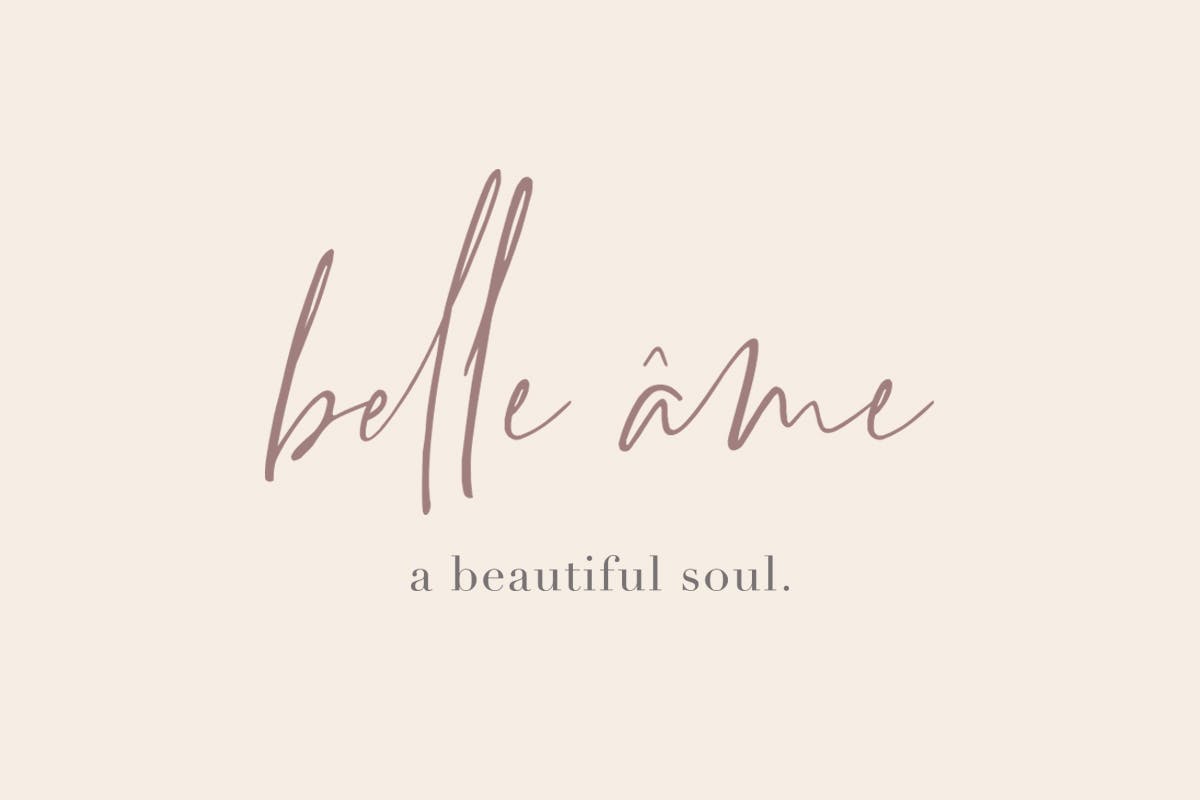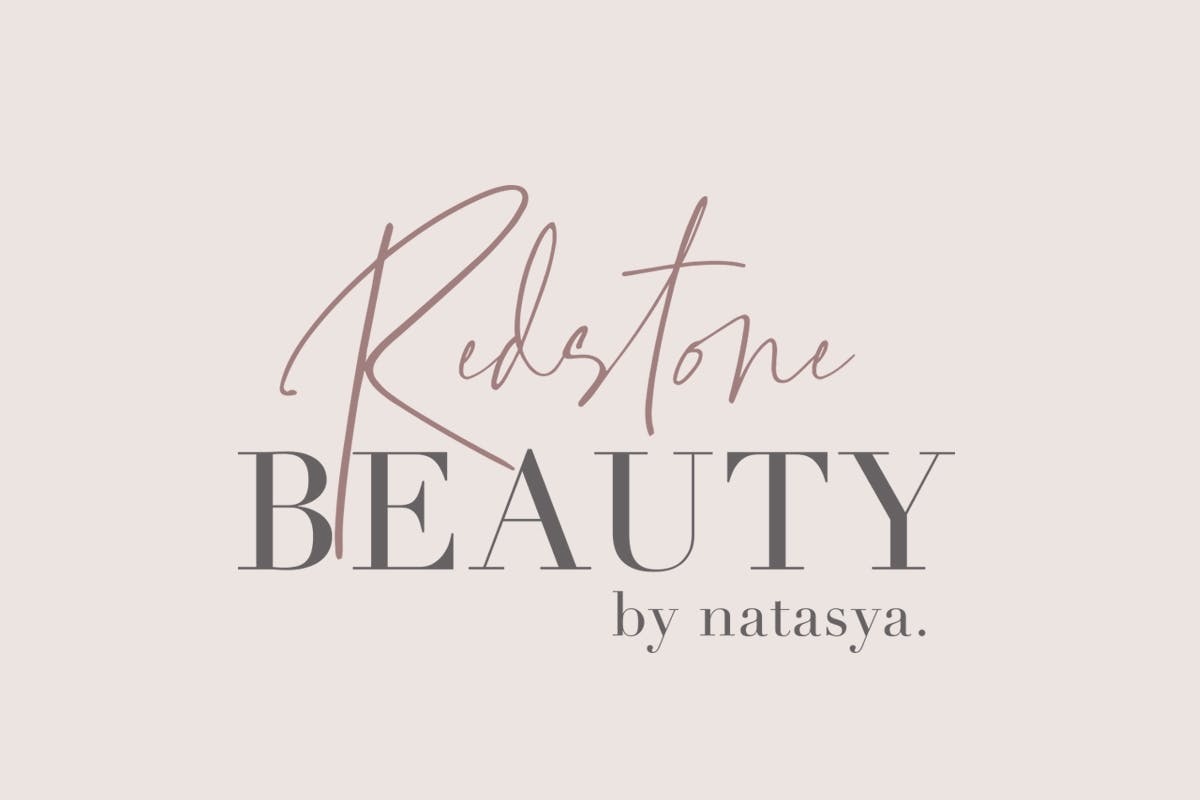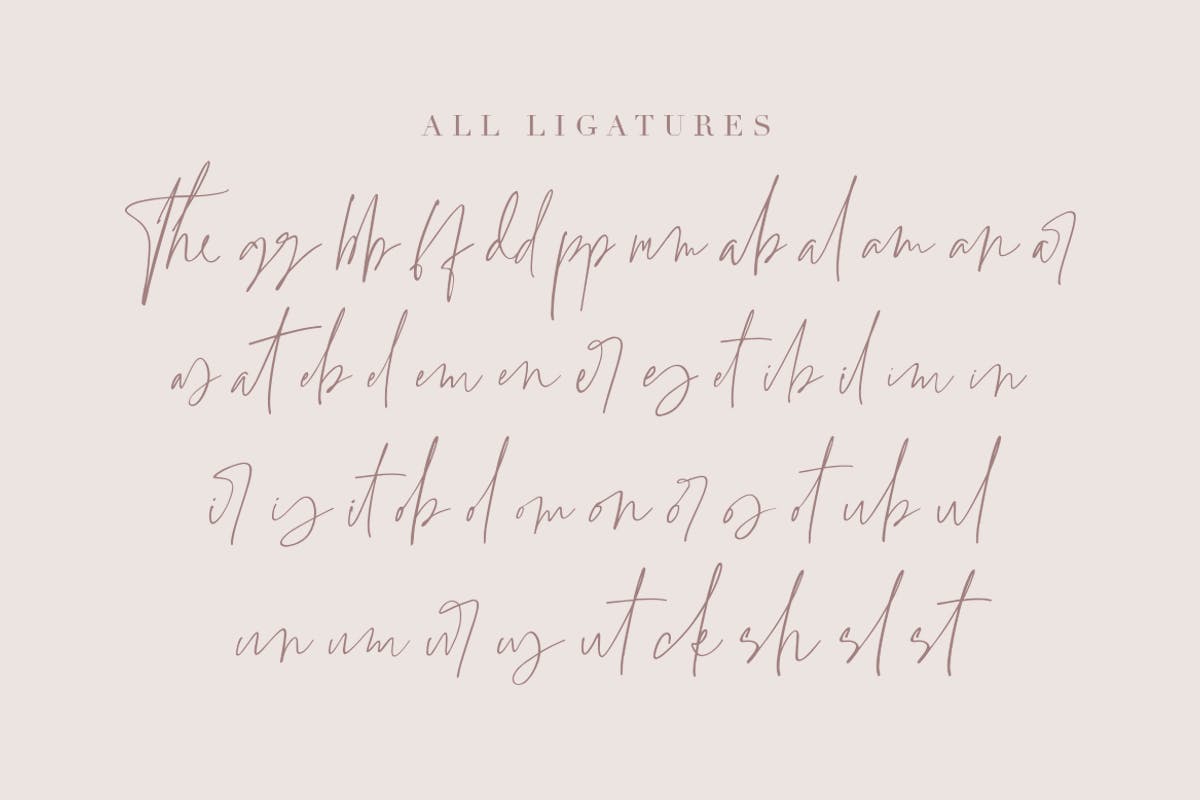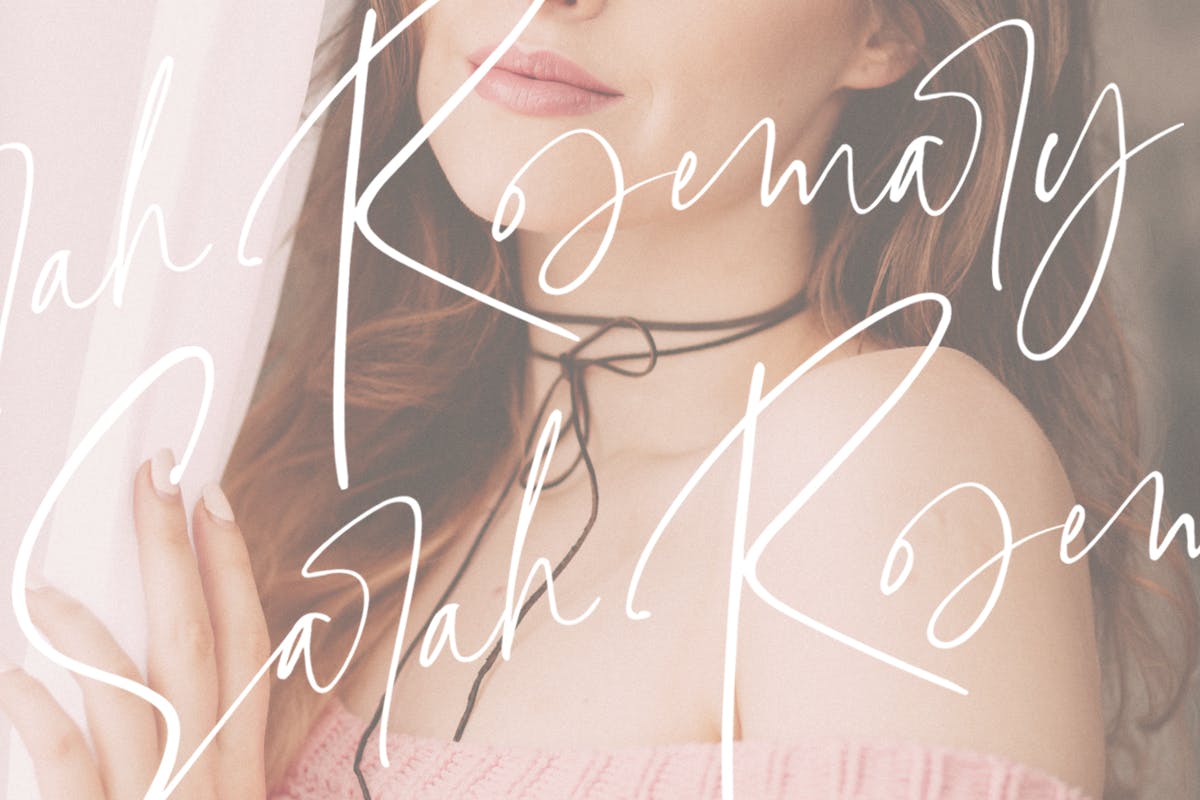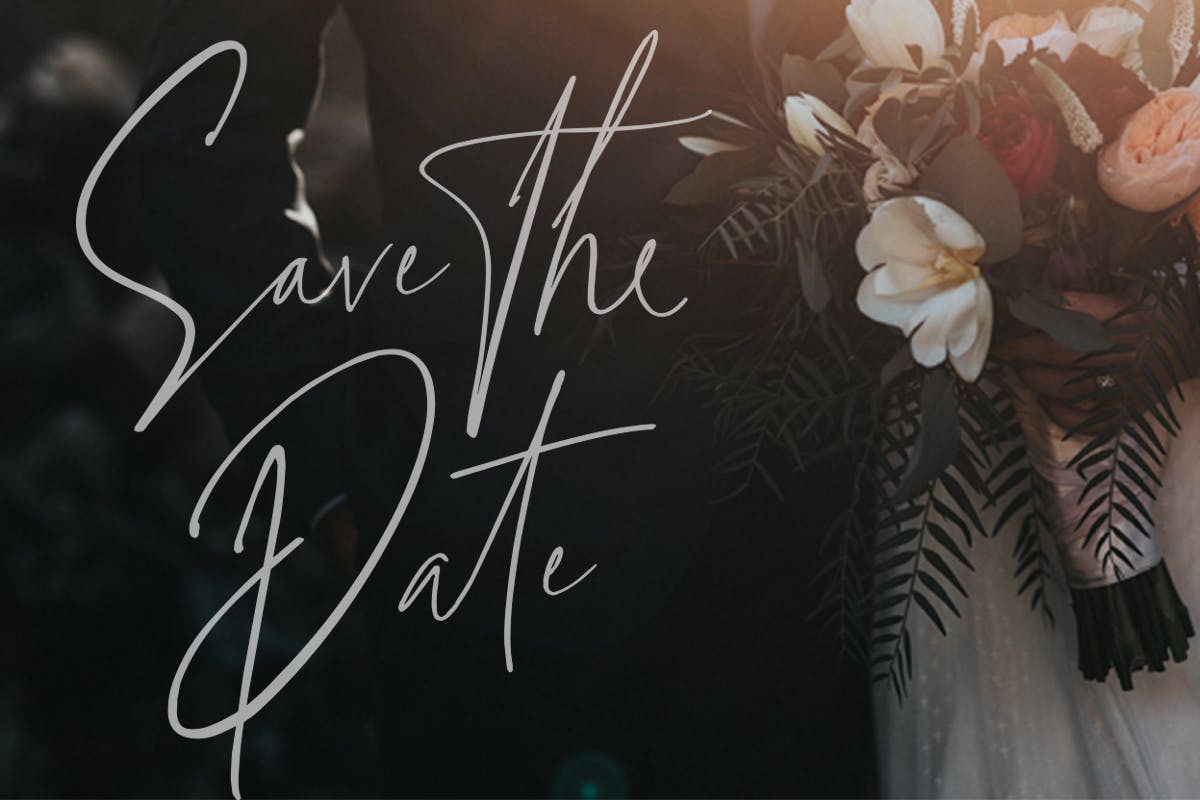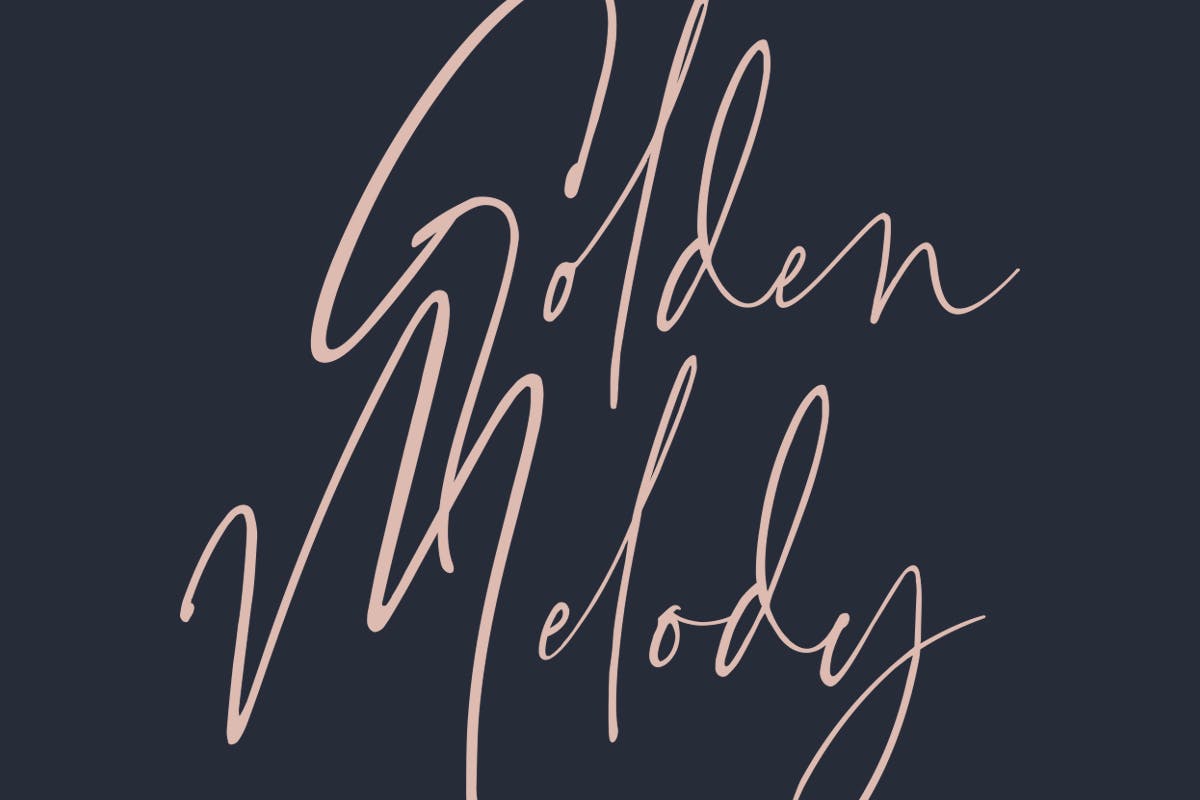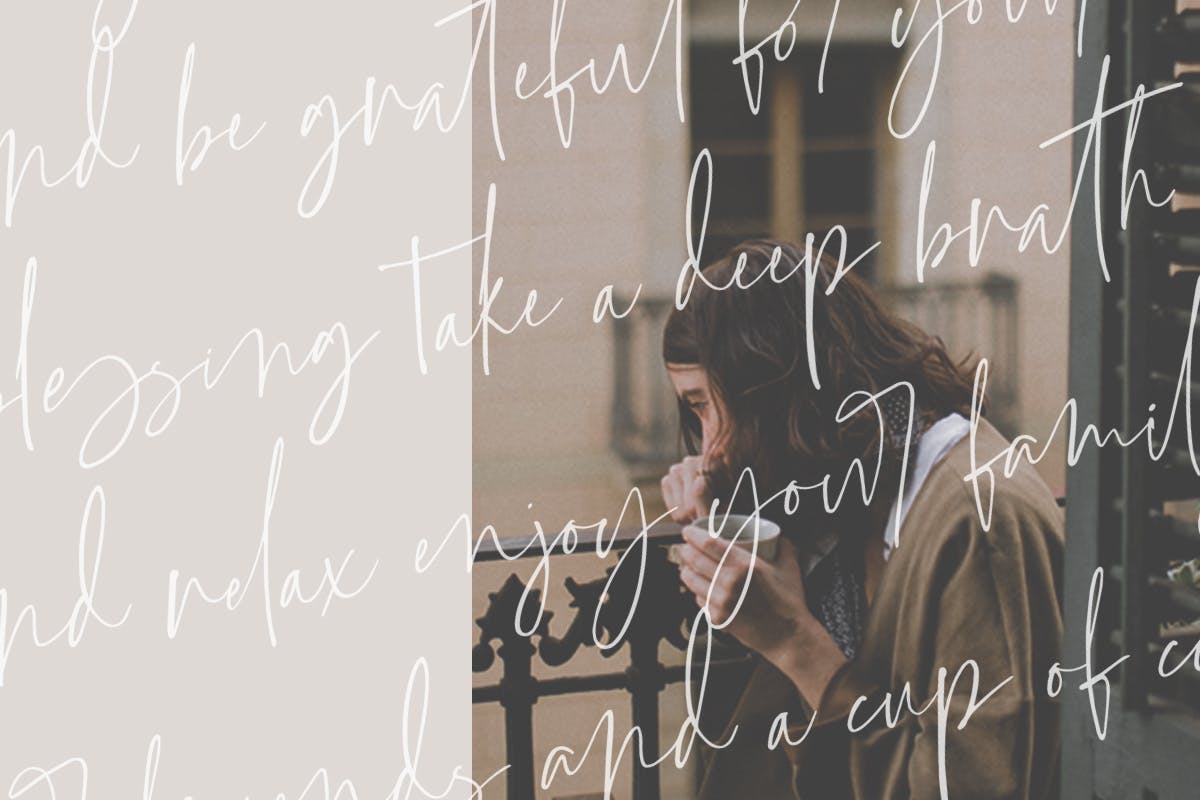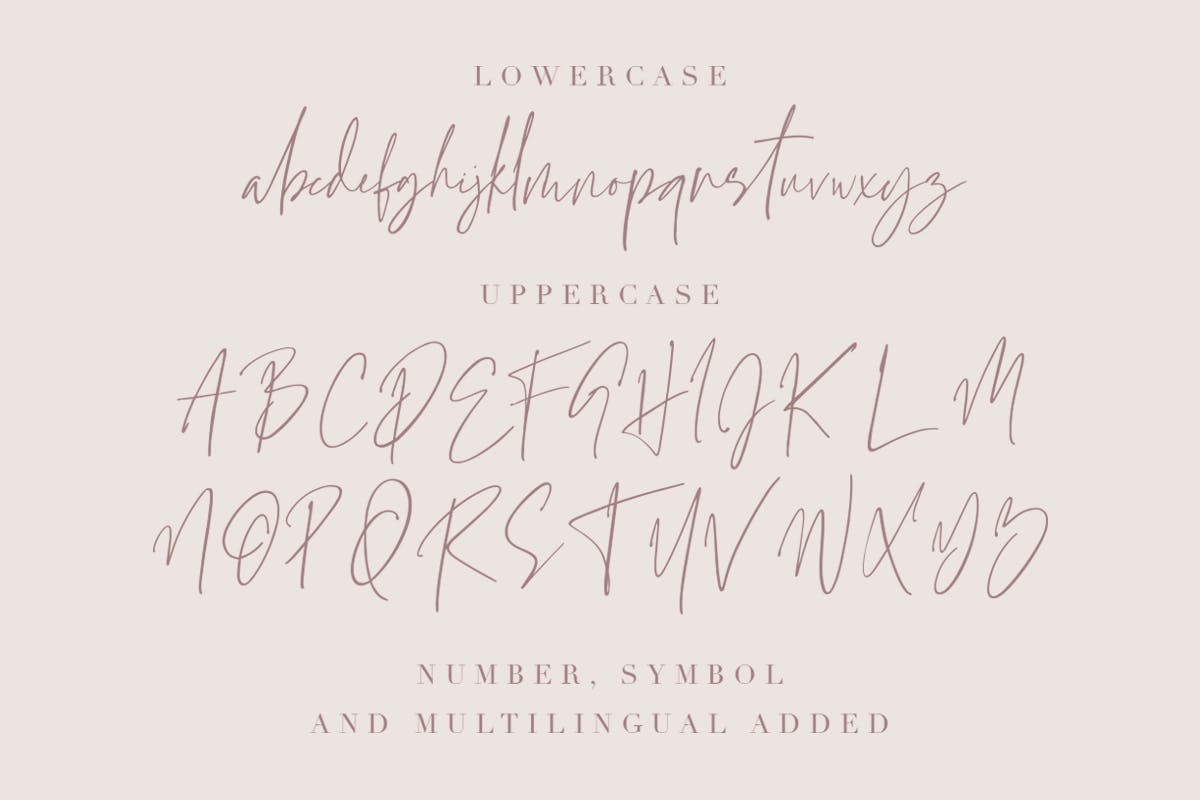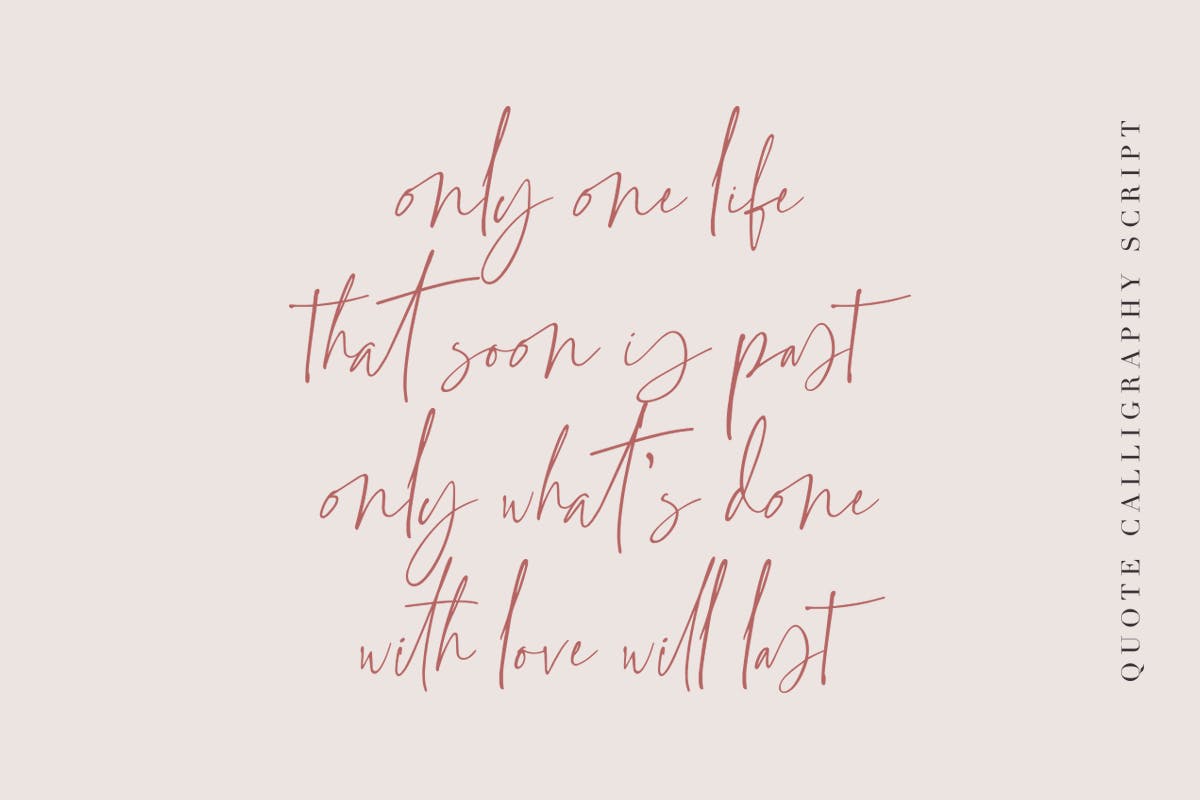
با فونت جدید و شیک Grandiose آشنا شوید!
این فونت با ترکیب شکلهای حروف شیک و چرخشی معاصر، انتخابی ایدهآل برای تمامی پروژههای لوکس شماست. این فونت برای طراحی لوگوهای شیک، نقلقولهای چاپی، کارتهای دعوت عروسی زیبا، هدرهای شبکههای اجتماعی، بستهبندی محصولات و بسیاری موارد دیگر مناسب است!
فونت Grandiose شامل مجموعهای کامل از حروف بزرگ و کوچک، نمادهای چند زبانه، اعداد و علامتهای نگارشی است. با بافت نرم جوهر مرطوب، این فونت برای انواع تکنیکهای چاپی مناسب است و میتوانید از آن برای گلدوزی، برش لیزری، طلاکاری و غیره استفاده کنید.